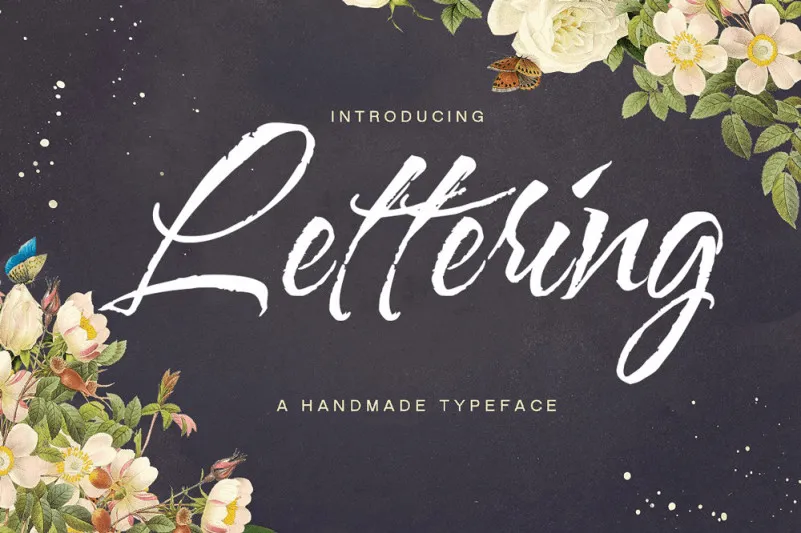
Lettering Script Font – Download Grátis
A Lettering Script é uma família de fontes modernas e pintadas a mão que transmitem aquela sensação casual mas convincente de autoria humana. Ela foi projetada para atender a uma variedade de necessidades, desde assinaturas até selos de newsletter e materiais de apresentação. Com sua aparência única e fresca, essa fonte é perfeita para aplicar na impressão dos seus projetos digitais ou físicos. Suas linhas fluidas e características distintivas fazem dela uma opção ótima para assinaturas pessoais, t-shirts personalizadas e até mesmo logotipos de casamento. Seja você um designer gráfico ou criativo que está buscando um toque único em seus projetos impressos, a Lettering Script é certamente o caminho a seguir.